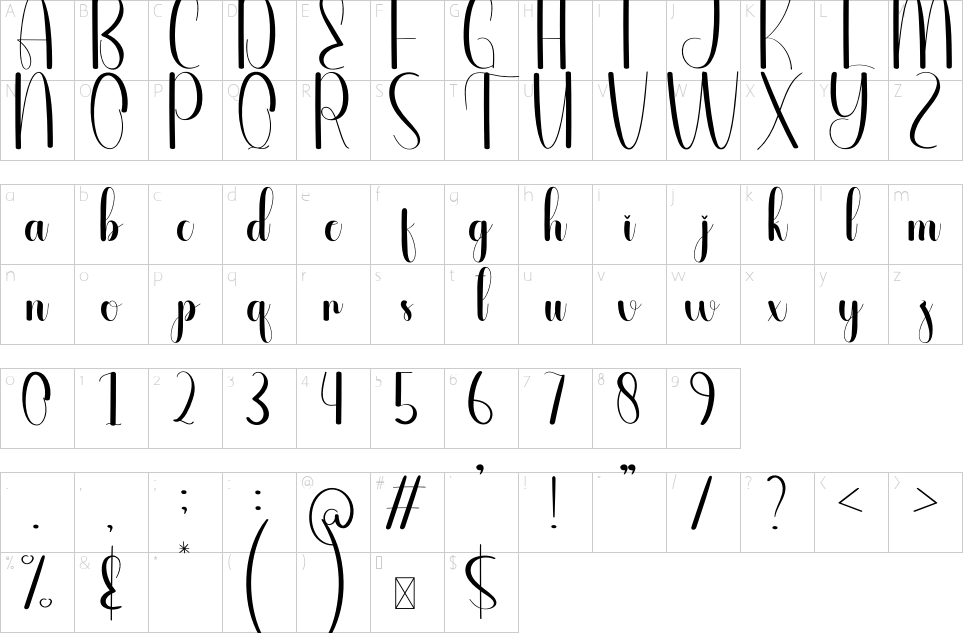
A fonte ‘Afraid Font’ é uma escolha perfeita para quem está procurando por uma fonte gráfica elegante e atraente, com um ar desconcertado e alegre que certamente deixará seu design pronto para uso. Desenvolvida pelo designer não informado, esta fonte é ideal para uso em projetos digitais e impressos. O download da Afraid Font foi feito várias vezes, evidenciando sua popularidade e qualidade. Ideal para estilos de design como o gráfico, web design e marca, a Afraid Font oferece uma escolha de 103 caracteres, incluindo símbolos especiais, permitindo que você personalize seu projeto para criar uma identidade visual única e moderna. Se você está buscando uma fonte que seja tanto funcional quanto atraente, a Afraid Font pode ser uma escolha perfeita.